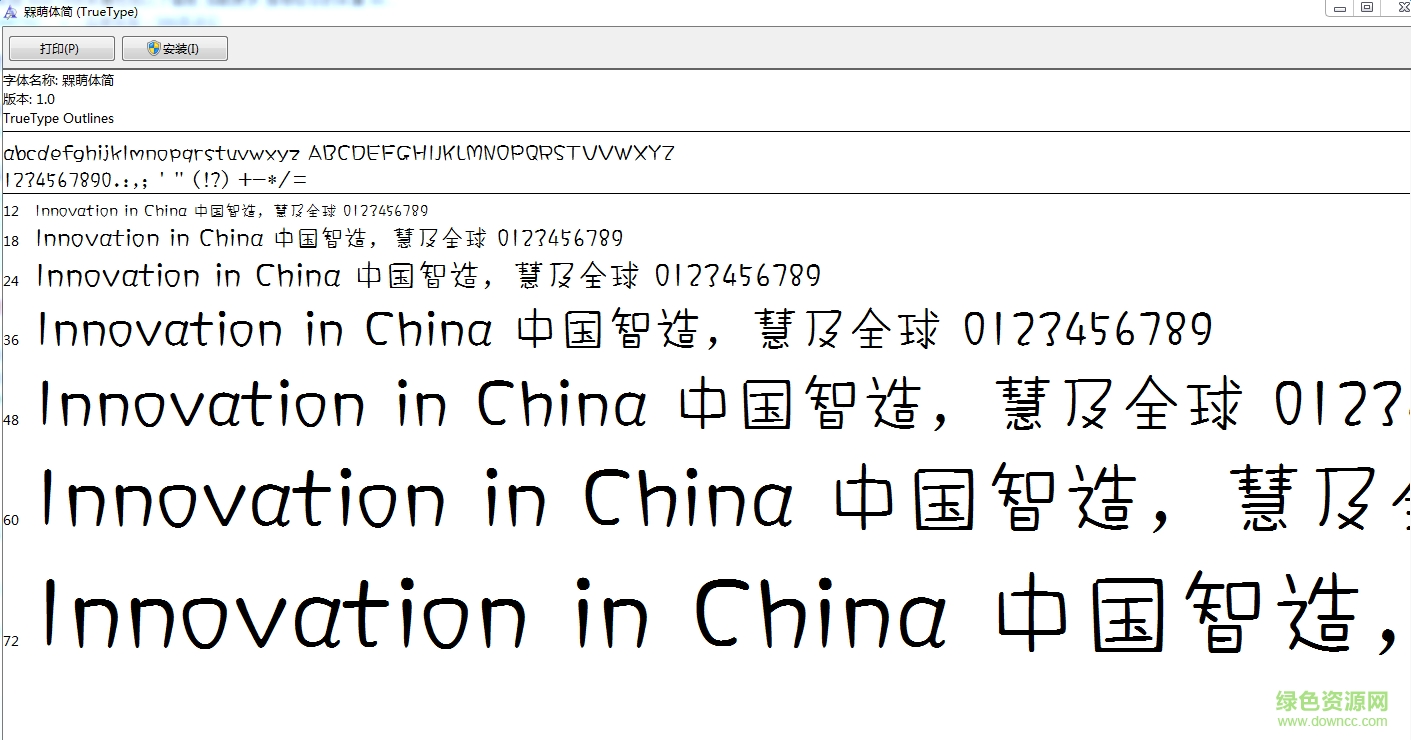
漢儀呆萌體又稱漢儀槑萌體簡體,是一款ttf格式的手寫版簡體字體,字體可愛清新,廣告設(shè)計(jì)、兒童海報(bào)、ppt等都可使用該款字體,喜歡的小伙伴歡迎在綠色資源網(wǎng)下載收藏!
漢儀呆萌體是一款兒童手寫風(fēng)格的藝術(shù)字體,字體筆畫帶有稚氣,活潑可愛,非常具有趣味性。整體效果十分出色。喜歡的朋友趕快下載吧。